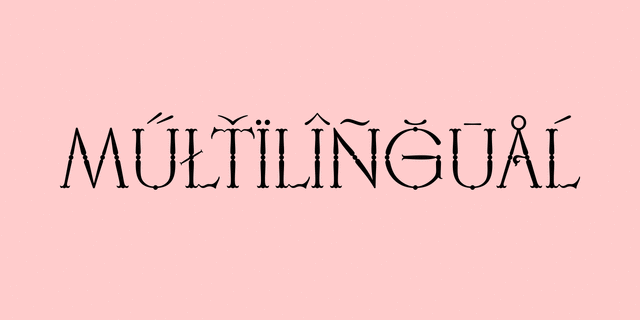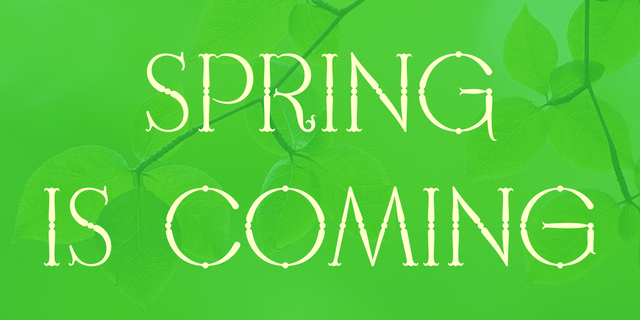
Франческа — изысканный декоративный шрифт, отлично подходит для торжественной и праздничной продукции. Разработан Лукьяном Турецким в 2015 году.
рыцарский, старинный, исторический, сказочный, волшебный, причудливый, изысканный, затейливый, забавный, мастерский, художественный, благородный, ювелирный, игривый, утонченный, красивый, выразительный, характерный, звонкий, прекрасный, ажурный, праздничный, музыкальный, колоритный, вкусный, торжественный, артистичный, королевский, элегантный, золотой, аристократичный, роскошный, богатый, романтичный, страстный
рыцарь, доспехи, свиток, музей, гравюра, миниатюра, искусство, история, одежда, театр, сказка, тату, татуировка, король, королева, украшение, ювелир, детская книжка, кафе, десерт, геральдика, музыка, волшебная сказка, ресторан, подарки, драгоценности, роскошь, антиквариат, булочная, любовь, вино, праздник, романтика, платье, замок, легенда, графика, иллюстрация Стилистика: